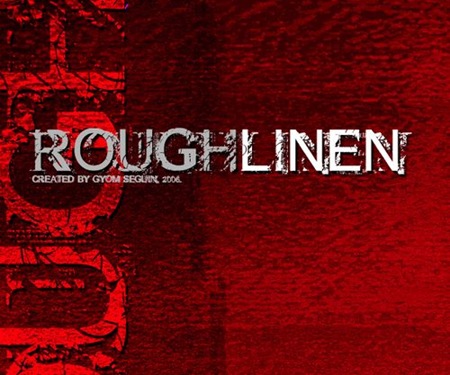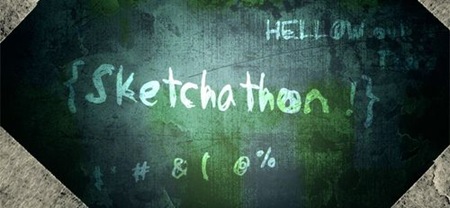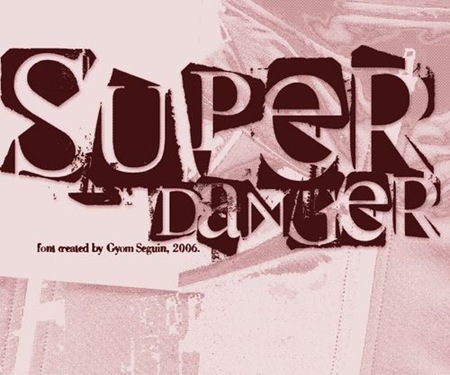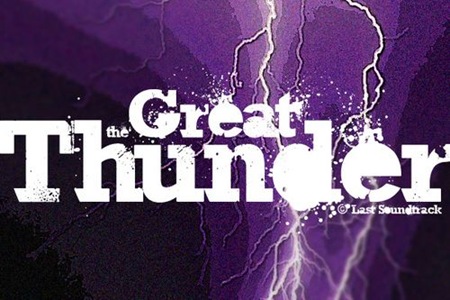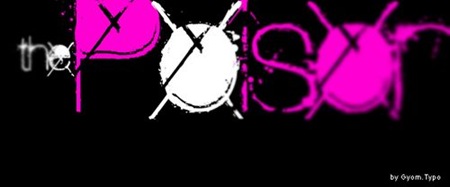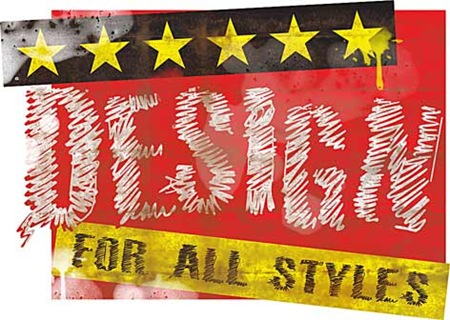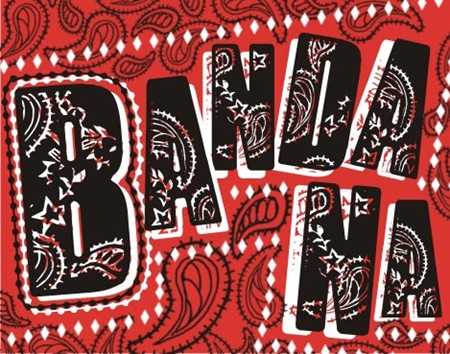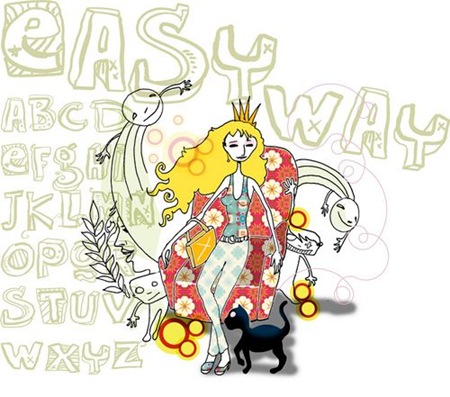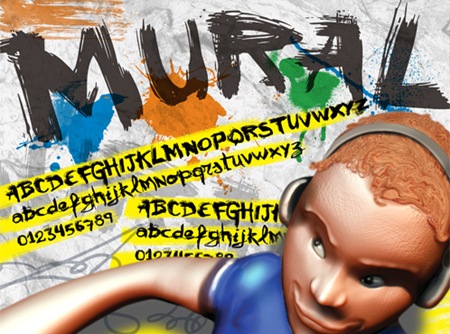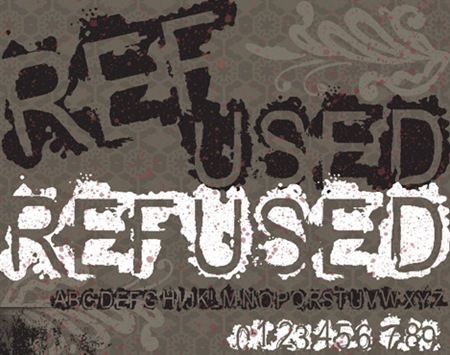
11 стильных бесплатных шрифтов
Шрифт “Rough Linen”
шрифт в стиле гранж
Шрифт “от руки” Sketchathon
Шрифт “от руки”
Гранжевый шрифт “Super Sanger”
гранжевый шрифт
Шрифт “The Great Thunder”
Шрифт с брызгами “The Poison”
Шрифт с брызгами
Шрифт-штрихи “VTKS 36”
Шрифт-штрихи
Шрифт с узорами “Bandana”
Шрифт с узорами
Забавный шрифт “Easy Way”
Забавный шрифт
Урбанистический шрифт “Mural”
урбанистический шрифт
Ретро шрифт “Refused”
Ретро шрифт
Шрифт в рок стиле “Rock garage band”
шрифт в стиле рок